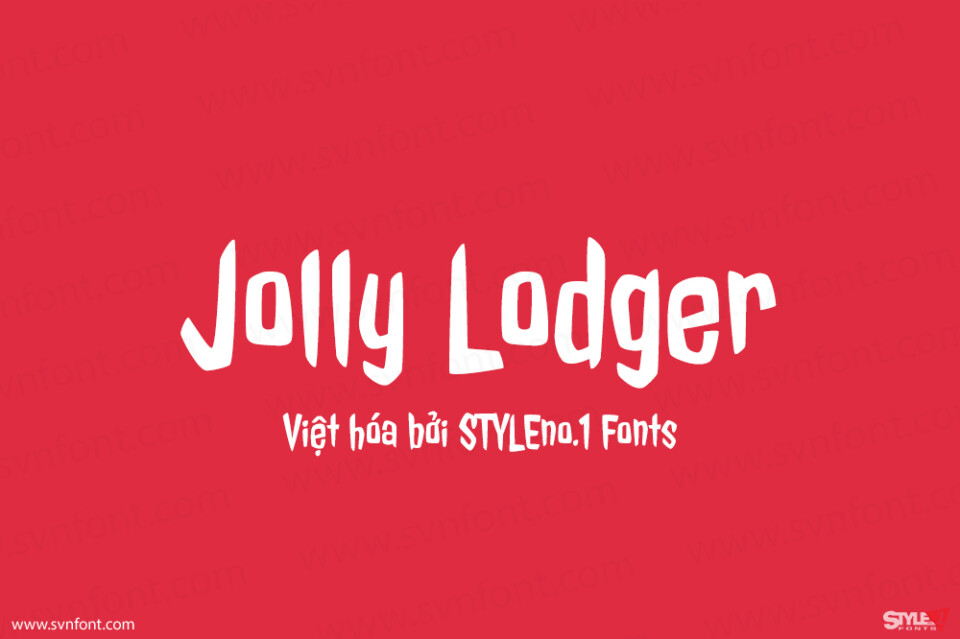
Font Việt hóa SVN Jolly Lodger
Giới thiệu về Font Việt hóa SVN Jolly Lodger
Trong thế giới thiết kế đồ họa, việc lựa chọn một bộ Font Miễn Phí phù hợp là yếu tố quyết định tạo nên sự thành công cho sản phẩm. Font Việt hóa SVN Jolly Lodger là một lựa chọn tuyệt vời dành cho những ai đang tìm kiếm sự phá cách và ấn tượng. Được lấy cảm hứng từ phong cách “Jolly Roger” truyền thống, bộ font này mang đậm hơi thở cổ điển nhưng vẫn giữ được nét tinh nghịch, phóng khoáng. Với các đường nét thanh mảnh nhưng sắc sảo, nó gợi liên tưởng đến những tấm biển quảng cáo ngoài trời tại các rạp xiếc hoặc phim kinh dị cổ điển của Mỹ những thập niên trước.
Tại sao nên sử dụng Font Việt hóa SVN Jolly Lodger?
Ưu điểm lớn nhất của Font Việt hóa SVN Jolly Lodger chính là khả năng thu hút thị giác cực mạnh ngay từ cái nhìn đầu tiên. Bộ font này đã được tối ưu hóa hoàn toàn cho tiếng Việt, giúp người dùng dễ dàng gõ các dấu câu mà không lo lỗi hiển thị. Đây là lựa chọn lý tưởng cho các biểu ngữ, tiêu đề phim, hoặc các thiết kế áo thun mang phong cách cá tính. Ngoài ra, tính linh hoạt của nó giúp các nhà thiết kế có thể ứng dụng trong nhiều dự án từ cổ điển đến hiện đại mà vẫn giữ được chất riêng biệt.
Cách ứng dụng Font Việt hóa SVN Jolly Lodger trong giáo dục và thiết kế
Đối với học sinh và giáo viên, việc sử dụng Font Việt hóa SVN Jolly Lodger trong các bài thuyết trình hay tờ rơi sự kiện trường học sẽ giúp nội dung trở nên sinh động hơn. Sự độc đáo trong cấu trúc chữ giúp kích thích sự sáng tạo và tạo không khí vui tươi cho môi trường học đường. Khi kết hợp với các tông màu rực rỡ, bộ font này thực sự tỏa sáng và truyền tải thông điệp một cách mạnh mẽ nhất. Hy vọng bạn sẽ có những trải nghiệm tuyệt vời khi sử dụng Font Miễn Phí, Font Việt Hóa, Font Việt hóa SVN Jolly Lodger cho các dự án sắp tới của mình.